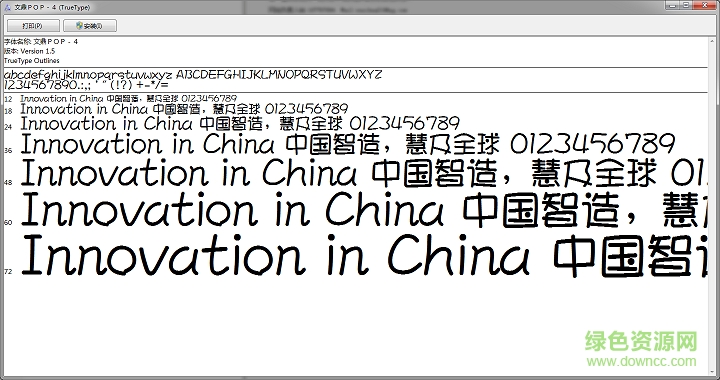
pop4eg bold gb字體是一款備受大家喜愛的文鼎pop-4簡體,字體結(jié)構(gòu)平穩(wěn),筆畫隨意,字形秀氣,看上去非常舒服,視覺效果不錯,需要的朋友快來綠色資源網(wǎng)下載吧!
字體優(yōu)美清新,線條流暢,給人以華麗柔美之感,此種類型的字體,適用于女用化妝品、飾品、日常生活用品、服務業(yè)等主題。